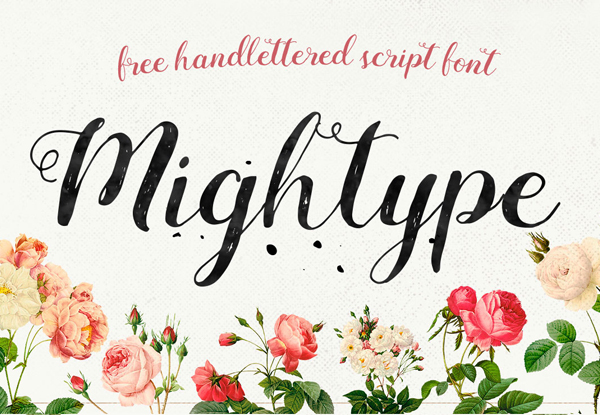
17个超时代风格字体
近段时间Ultramodern风格,即超时代风格,其实我一直认为这种风格是前卫风格,使用线型或大跨越字体,彰显个性的风格设计理念。
Cast Iron Free Font
Cast Iron Font Letters and Numbers
Ansley Display Free Font
Ansley Display Font Letters and Numbers
Kilauea Free Font
Kilauea Font Letters and Numbers
Cornerstone Free Font
Cornerstone Font Letters and Numbers
Mightype Script Free Font
Mightype Script Font Letters and Numbers
Neaments Free Font
Neaments Font Letters and Numbers
Talisman Free Font
Talisman Font Letters and Numbers
Arcadia Free Font
Arcadia Font Letters and Numbers
One Way Free Font
One Way Font Letters and Numbers
Devious Free Font
Devious Font Letters and Numbers
Simple Free Font
Simple Font Letters and Numbers
Stilu Free Font
Stilu Font Letters and Numbers
Wings of Darkness Free Font
Wings of DarknessFree Font
Wings of Darkness Font Letters and Numbers
Dreamers Brush Free Font
Dreamers Brush Font Letters and Numbers
WalkOn Free Font
WalkOn Font Letters and Numbers
PLUME Free Font
PLUME Font Letters and Numbers
Creditverse Free Font
Creditverse Font Letters and Numbers